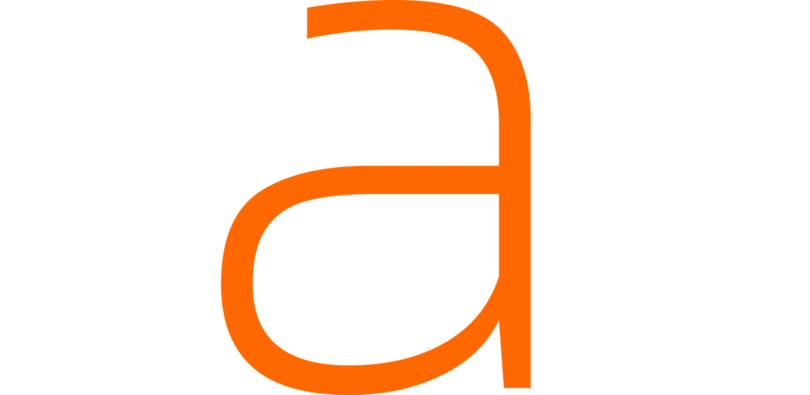
Die neue Schrift der Alibaba Group bringt Stil und Einfachheit in das Ökosystem des Unternehmens.
„ Monotype verstand unsere einzigartigen Herausforderungen und lieferte uns eine Schrift, die uns bei unseren Branding-Bemühungen auf die nächste Stufe bringen wird. “
Alibaba Sans
Die speziell entwickelte Schriftfamilie Alibaba Sans verbindet Partner und Kunden durch eine markentreue Ästhetik.
Die Herausforderung
Das Corporate Branding-Team der Alibaba Group hatte mit einer Vielzahl von Design-Herausforderungen zu kämpfen, da verschiedene Open-Source Schriften im Einsatz waren: bei den Kreativteams, in Niederlassungen und natürlich im gesamten Ökosystem der digitalen Partner und Lieferanten.
Das rasche Wachstum der Handelsplattform weckte den Bedarf nach einer konsistenten, flexiblen und innovativen Schrift, die es den Designern erlaubt, frei zu experimentieren und gleichzeitig die Richtlinien der Marke und deren geistiges Eigentum bewahren. Angesichts der Natur des E-Commerce und des Einzelhandels als Kerngeschäft benötigte das Unternehmen eine Schrift, bei der die Ziffern und die Währungssymbole eine enorme Rolle spielen, und natürlich auch die Buchstaben. Eine weitere Herausforderung bestand darin, dass die Alibaba Group ihre Hausschrift problemlos mit Kollegen, Partnern und Kunden in einem dynamischen Markt teilen muss, um markengerechte Kampagnen zu erstellen.
Die Lösung
Die Designteams von Monotype und der Alibaba Group setzten eine Reihe mehrtägiger Workshops in Gang, um in kürzester Zeit ein maßgeschneidertes Schriftkonzept zu entwickeln, das die Unternehmenspersönlichkeit der Alibaba Group verkörpert.
Unter der Leitung von Type Director Akira Kobayashi begann das Monotype Studio damit, die Anforderungen der Alibaba Group zu lösen, indem es zunächst Ziffern und Währungssymbole entwarf, die für den E-Commerce Bereich des Konzerns von entscheidender Bedeutung sind. Das Team zeichnete für Alibaba Sans die Zahlen und alle Buchstaben von Grund auf neu, einschließlich des einzigartigen Kleinbuchstabens a aus der Logotype. Das Schriftbild mussten selbst bei den stärksten Strichstärken angenehm für das Auge sein und von klein bis groß auf jedem Gerät und an jedem Ort lesbar: auf den Bildschirmen, den Leitsystemen mehrere Bürogebäude, im Souvenirladen des Unternehmens, den Einkaufszentren und den E-Commerce- Websites weltweit.
Auf Basis der Ergebnisse einer weltweiten Mitarbeiterbefragung, bei der die wichtigsten Begriffe ermittelt wurden, die Alibaba repräsentieren, orientierte sich das Design von Alibaba Sans an den Markenwerten „leidenschaftlich“, „kraftvoll“ und „zukunftsorientiert“. Die Exklusivschrift wurde auf dem UCAN-Festival von Alibaba Design am 27. und 28. April 2019 vorgestellt. Dort wurde der neue typografische Baukasten mit Freude aufgenommen: „Endlich können wir unsere Angebote schön und einfach in Szene setzen“, lautete das gemeinsame Fazit.
„ Monotype hat unsere einzigartigen Herausforderungen verstanden und uns eine Schrift geliefert, die Alibaba bei seinen Branding-Bemühungen auf die nächste Stufe hebt. Wir schätzen die Partnerschaft mit Monotype sowie deren Expertise als Ergänzung unseres Teams sehr. Wir werden die neue Schrift allen Partnern und Kunden weltweit zur Verfügung stellen, und zwar kostenlos. “
Ergebnisse
Intern:
• Bereitstellung einer konsolidierten und konsistenten typografischen Identität für das gesamte Business
• eine hochwertige, vielseitige Originalschrift zum Experimentieren und Entwerfen außergewöhnlicher Kampagnen
• Benutzerfreundlichkeit über alle Design-Touchpoints hinweg
• Schaffung eines kohärenten Markenimages und einer unverwechselbaren Unternehmenspersönlichkeit
• Auflösung von Irritationen, da alle Kunden und Partner die neue Schrift an allen Touch-Points wiedererkennen und verwenden
• Kostenlose Bereitstellung der neuen Schrift für alle, um das markengerechte Design schnell zu etablieren
„ Die Alibaba Group stand vor einer typischen, aber auch anspruchsvollen Markenherausforderung, da sie ihre Markenwerte in einer Vielzahl von Umgebungen kommunizieren musste, sowohl physisch als auch digital. Es war ein Vergnügen, mit einem Team zusammenzuarbeiten, das sich so sehr der Bedeutung der Schrift bewusst war, und der Alibaba Group dabei zu helfen, das Potenzial zu erkennen, das eine individuelle Schrift für die Identität einer Marke hat. “
Akira Kobayashi, Type Director, Monotype